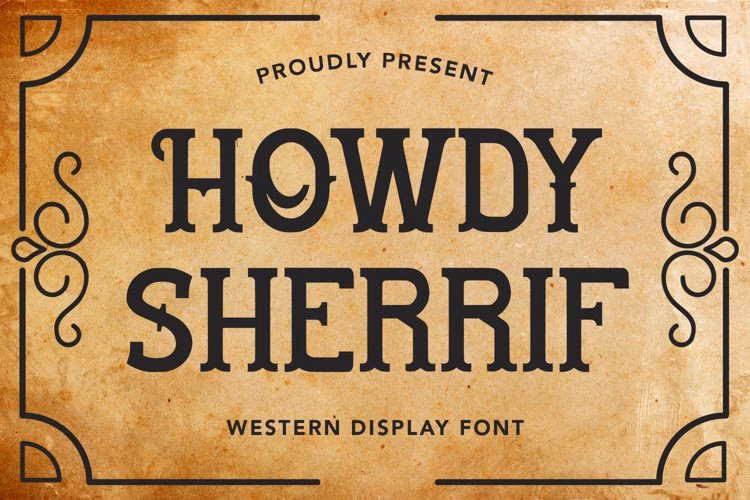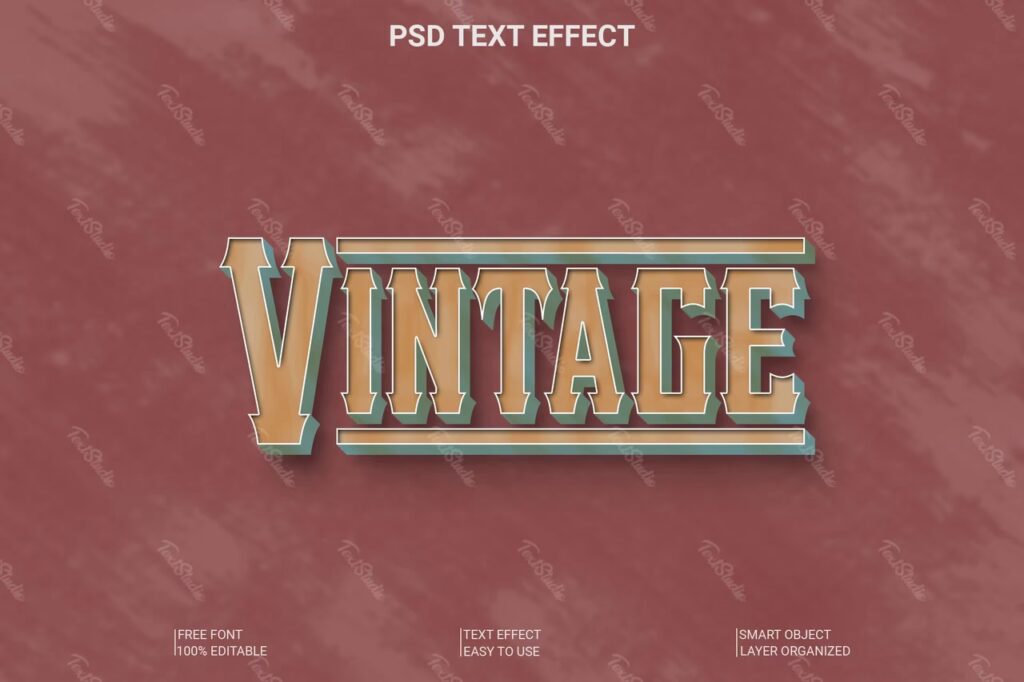
Den æstetiske stil fra Det Gamle Vesten er en trend, der aldrig rigtig går af mode. Ligesom de klassiske westernfilm, der stadig fanger publikum, har denne stil en vedvarende appel inden for design. Et af de mest afgørende elementer for at skabe det autentiske western-look er brugen af den rette skrifttype. Western skrifttyper er ikke bare bogstaver; de bærer en følelse af historie, eventyr og den rå skønhed fra prærien.
Disse skrifttyper er utroligt populære og alsidige. De ses ofte i logodesign, på badges, produktetiketter, plakater, filmtitler og meget mere. De formår at tilføre et design karakter og en unik stil, der skiller sig ud fra mere moderne skrifttyper. Uanset om du sigter efter et barskt cowboy-look til en filmplakat eller en vintage western-stil til et logo, findes der en skrifttype, der passer perfekt.
Hvad er Karakteristisk for Western Skrifttyper?
Western skrifttyper henter inspiration fra typografien brugt i slutningen af 1800-tallet og begyndelsen af 1900-tallet i USA. De associeres ofte med saloonskilte, avisforsider, og ikke mindst, "Wanted" plakater. Deres design er typisk modigt og iøjnefaldende, designet til at fange opmærksomhed. Nogle af de mest genkendelige træk inkluderer:
- Slab Serifs: Kraftige, blokformede seriffer (ender på bogstaverne), der giver et solidt og robust udseende.
- Dekorative Elementer: Mange western skrifttyper indeholder udsmykninger, såsom sporer (små udstikkere) på serifferne eller krøller, der tilføjer et vintage eller victoriansk præg.
- Fed og Komprimeret: Ofte er bogstaverne meget brede og fede, men kan også være komprimerede i bredden for at spare plads på skilte og plakater.
- Rustik Tekstur: Nogle designs inkorporerer en tekstur, der efterligner gamle træskilte eller tryk fra ældre trykpresser.
- Alle Store Bogstaver: Mange klassiske western skrifttyper er designet primært eller udelukkende med store bogstaver (versaler).
Disse træk kombineres for at skabe en følelse af autenticitet, nostalgi og en forbindelse til den amerikanske pionertid.
Anvendelsesområder for Western Skrifttyper
Western skrifttyper er utroligt alsidige og kan bruges i en bred vifte af designprojekter. Deres evne til at tilføre karakter og en stærk visuel identitet gør dem ideelle til:
- Branding og Logoer: Skab et mindeværdigt og karakterfuldt brand, især for virksomheder med et rustikt, håndværksmæssigt eller amerikansk tema (f.eks. bryggerier, BBQ-restauranter, tøjbutikker).
- Plakater og Flyers: Fang øjet med fed typografi til events, koncerter, filmplakater eller reklamer, der kræver et vintage eller iøjnefaldende look.
- Produktemballage og Etiketter: Design etiketter til fødevarer, drikkevarer (især øl og whisky), eller andre produkter, hvor et autentisk, håndværksmæssigt eller historisk udseende ønskes.
- Bogomslag og Redaktionelt Design: Perfekt til historiske romaner, westerns eller publikationer, der ønsker at formidle en specifik tidsperiode eller stemning.
- Skiltning: Efterlign udseendet af gamle butiks- eller saloonskilte for en autentisk atmosfære.
- Beklædning: Design T-shirts, hatte eller andet tøj med tryk, der bruger western-inspireret typografi.
Et Udvalg af Bemærkelsesværdige Western Skrifttyper
Der findes et enormt udvalg af western skrifttyper, der hver især tilbyder deres egen unikke fortolkning af stilen. Nogle læner sig tæt op ad de historiske forbilleder, mens andre tilføjer et moderne twist. Her er et kig på nogle eksempler, der illustrerer bredden i denne kategori:
- Bozorg: En fed slab-serif med et moderne twist på klassisk western-stil. God til branding og titler.
- The Wildtern: En gammel western-stil font med smukke dekorative elementer, der minder om 17. århundredes typografi. Tilbyder mange alternative tegn.
- Desert Western: En moderne serif med stærk kontrast mellem tykke og tynde linjer, let læselig.
- La Losarito: En blanding af mexicanske vintage-elementer og moderne stil, fed og dekorativ. Kun store bogstaver.
- Cowboy Clasico: En ægte dekorativ gammel western-stil, velegnet til branding og plakater.
- Roseblade: Inspireret af vintage elegance og fare, med intrikate, tornlignende detaljer. God til bogomslag og invitationer.
- Dezieg: En western-stil font med store bogstaver, påvirket af rodeo-plakater, med kraftige kanter.
- Gunslinger: En gammel western-stil font, der tilføjer cowboy-charme, ideel til logoer, citater og invitationer.
- Horse Belonk: En font med kun store bogstaver og et gammelt vesten-look, inkluderer en extrude-font for 3D-effekter.
- Strong West: En tattoo-stil font med klassisk western-design, god til skiltning og emballage.
- Westimor: En klassisk western-font med retro-design, ideel til titler og logoer. Fås i flere stilarter.
- Western Cowboy: Bruger et vintage bogstavsdesign til at ligne noget fra en gammel westernfilm, mange alternative funktioner.
- Gold Coast: En klassisk gammel western-font, der minder om gamle westernfilm, store fede bogstaver med mange alternative tegn.